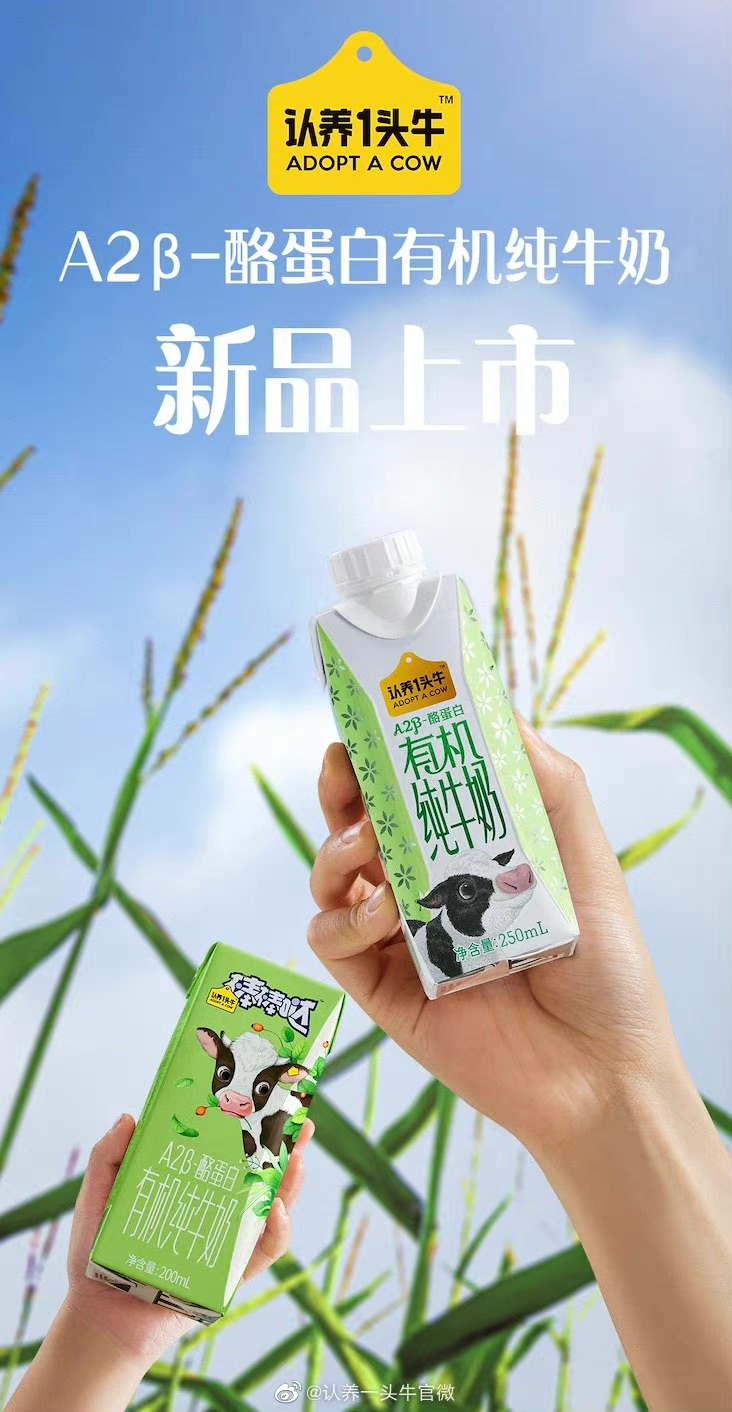
方正李邕行书
行书
关于李邕:
李邕(678~747年),唐代书法家。字泰和,出身江夏李氏,博学多才,少年成名。书法初学王羲之,后摆脱旧习,笔力一新,有“右军如龙,北海如象”之喻。作为行书碑文大家,书法风格奇伟倜傥。传世有碑刻《麓山寺碑》、《叶有道先生碑》、《端州石室记》、《云麾将军碑》,传世墨迹有《出师表》等。
字体特征:
以李邕《麓山寺碑》、《出师表》为主要临创开发依据,字体笔画瘦劲有力,方圆兼备,结构宽博,向四面开放,中宫紧缩,于奇险中见庄严,气势豪迈雄健。
应用场景:
电商、品牌、海报、杂志、书籍、包装、广告、招牌、新媒体、影视、动漫等